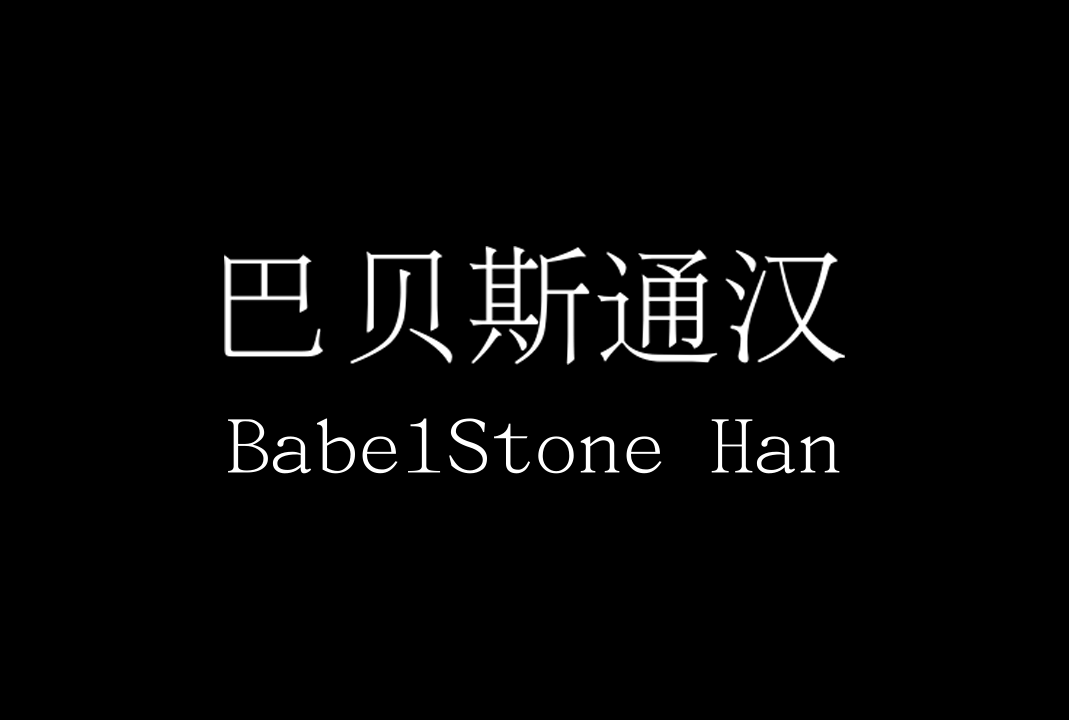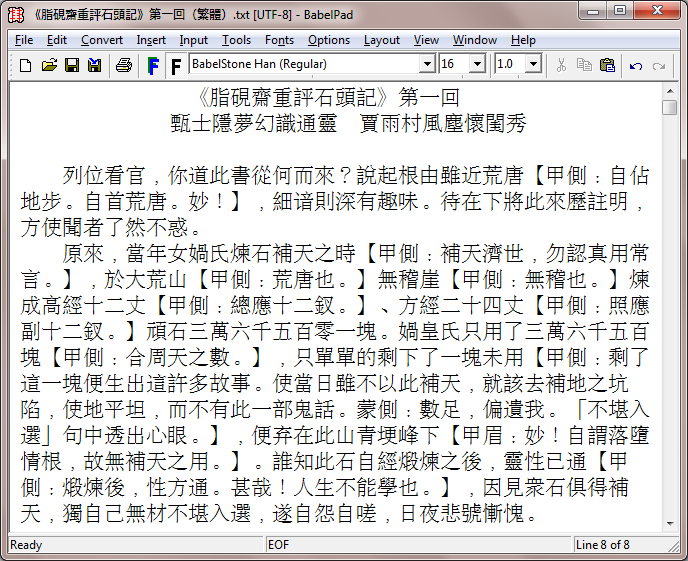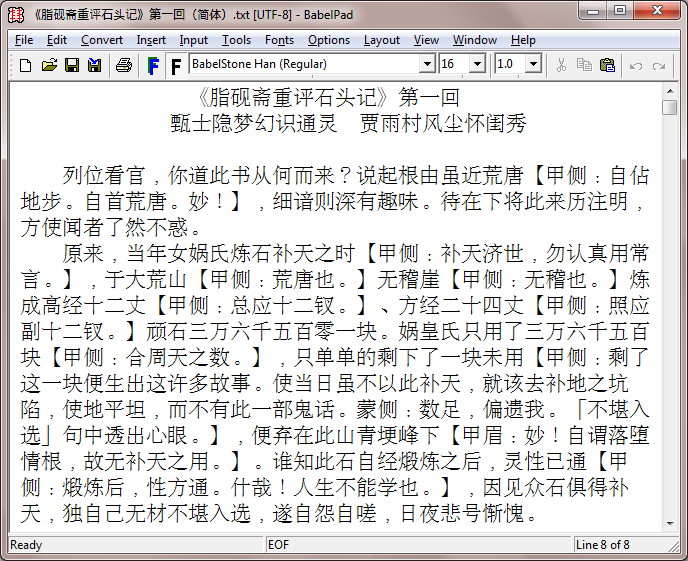
巴贝斯通汉(BabelStone Han )是一种宋体/明体(Song / Ming)风格的字体,其字形以中华人民共和国使用的正式字符形式为原型。
巴贝斯通汉(BabelStone Han )包含许多稀有或古旧字符的宋明体风格字体,是一种免费的 Unicode CJK 字体,具有 41,000 多个汉字(hanzi,kanji,hanja),总共超过52,000个Unicode字符。它涵盖了中文繁体汉字和简体汉字、日韩,并且包括许多大多数CJK字体中找不到的稀有或古旧字符,以及用于书写壮语的上千个Sawndip字符。在专用区(PUA)中还包括3,700多个未编码的汉字。
中文繁体示例
中文简体示例